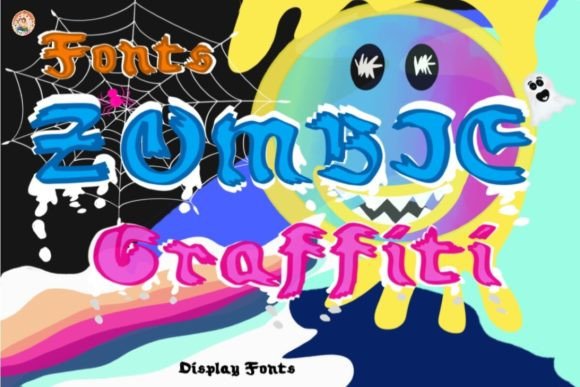
Zombie Graffiti Fonts
Zombie Graffiti Fonts – A Fonte Que Transforma Seu Design
Se você está em busca de uma tipografia que combine o estilo urbano com um toque assustadoramente criativo, Zombie Graffiti Fonts é a escolha perfeita. Essa fonte única traz a energia do grafite de rua e o charme dos zumbis, tornando‑a ideal para quem deseja destacar convites, papelaria, postagens em redes sociais e cartões de felicitações.
Por que usar Zombie Graffiti Fonts?
- Versatilidade visual: funciona tanto em projetos elegantes quanto em criações descontraídas.
- Impacto imediato: letras com contornos desgastados e detalhes de “sangue” atraem o olhar e aumentam a taxa de engajamento.
- Alta legibilidade: apesar do estilo “zumbi”, a fonte foi otimizada para garantir leitura clara em diferentes tamanhos.
Aplicações Ideais
Com Zombie Graffiti Fonts você pode criar:
- Convites de festas temáticas – de Halloween a festas de “apocalipse zumbi”.
- Papelaria personalizada – cartões, agendas e blocos de notas com um visual inesquecível.
- Posts para Instagram, TikTok e Facebook que geram curtidas e compartilhamentos.
- Cartões de felicitações criativos – um toque divertido que surpreende quem recebe.
- Arte digital e ilustrações – adicione uma camada de personalidade às suas composições.